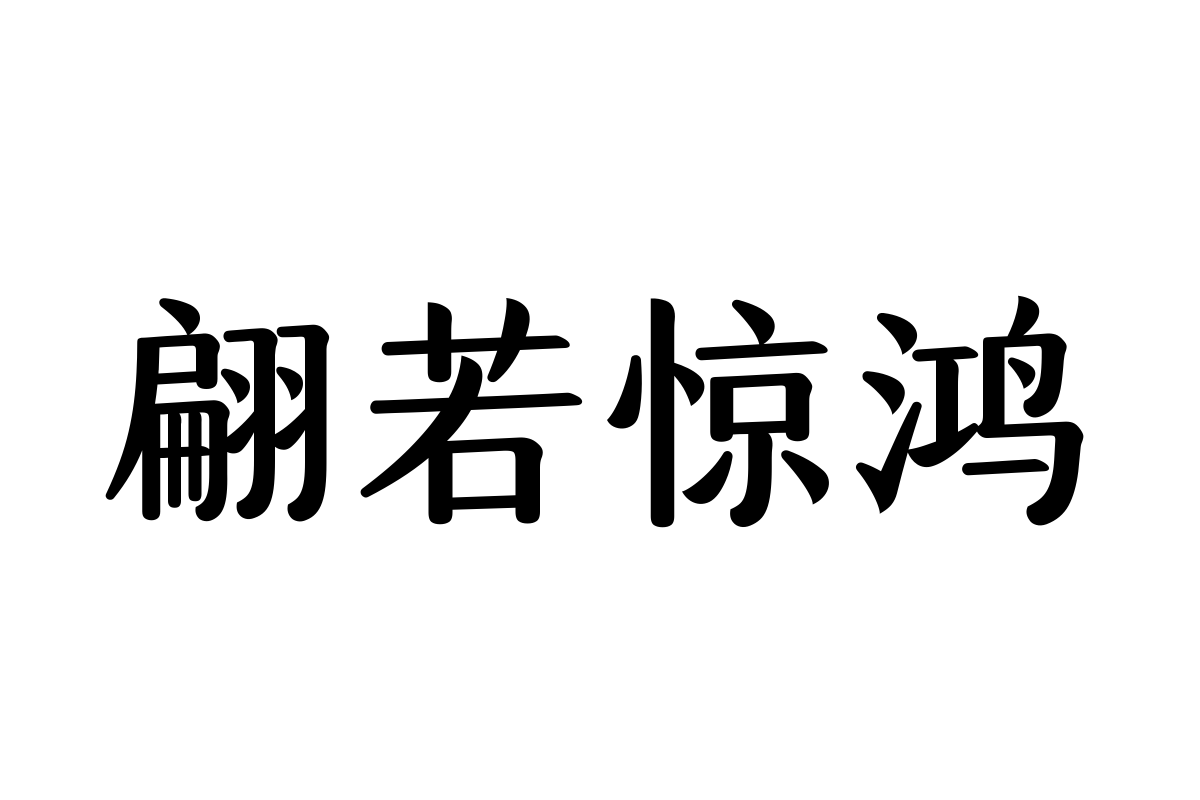
汉仪空山楷 W 字体是一款具有独特风格的书法字体,它结合了传统的楷书结构和现代的设计理念,创造出一种既典雅又现代的视觉效果。这款字体的特点是笔画流畅、结构严谨,既有楷书的规矩感,又不失灵动和个性。
在字形上,汉仪空山楷 W 字体采用了简洁而有力的线条,使得整个字体看起来更加清晰和易读。同时,该字体还注重细节的处理,如笔锋的变化、墨色的深浅等,都经过精心设计,使得每个字都能展现出独特的韵味和美感。
除了字形上的创新,汉仪空山楷 W 字体还在风格上进行了大胆的尝试。它摒弃了传统楷书中常见的繁复装饰,而是采用了简约的设计,使得整个字体更加干净、利落。同时,该字体还融入了一些现代元素,如不规则的笔画、抽象的形状等,使得整体风格更加多元化和个性化。
总的来说,汉仪空山楷 W 字体是一款极具创意和艺术性的书法字体,它不仅能够为设计师提供丰富的灵感和素材,还能够为读者带来愉悦的阅读体验。无论是用于书籍、杂志还是网页设计,这款字体都能够展现出其独特的魅力和价值。